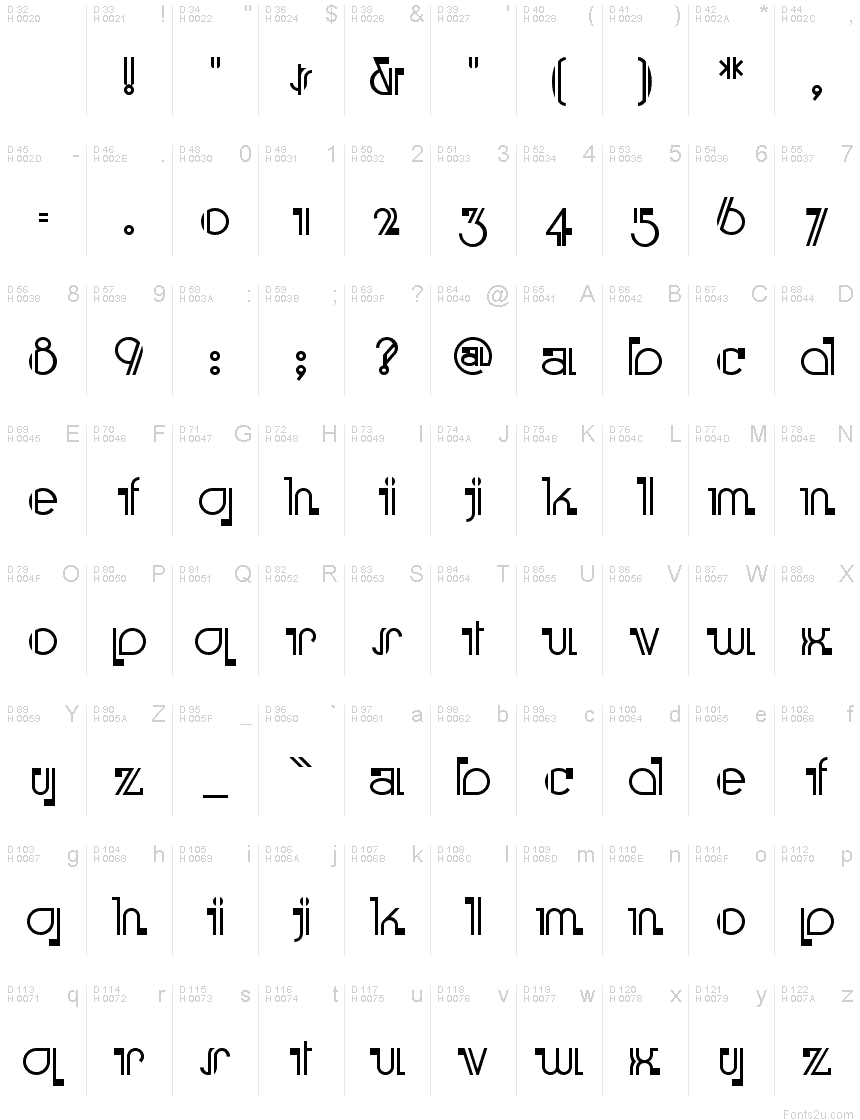
BooMeringueNF
Nick's Fonts
Nick Curtis
来自 Nick's Fonts 的 Nick Curtis 所设计的 Boo Meringue NF 是一款免费的复古显示字体,它能将任何文字转化为一种循环往复的动态图案。字形在圆润的曲线与方正的棱角之间游走,垂直的切口在黑色中凿出明亮的白色光束,宛如光线穿过百叶窗。这种韵律感几乎令人着迷:重复的弧线、如回力标般的曲线以及高耸的笔画,在你的文本行中堆叠出整洁、模块化的天际线效果。
使用 Boo Meringue NF,你将获得一种大胆的复古未来主义风格,非常适合海报、专辑封面、标志设计、活动视觉、醒目的包装以及科幻或电子风格的标题。这款免费字体在字号较大时表现最佳,其切割曲线与紧密的重复结构能得到充分展现。建议将 Boo Meringue NF 与一款简约的几何无衬线字体搭配用于正文,以确保主标题依然醒目且独具辨识度。